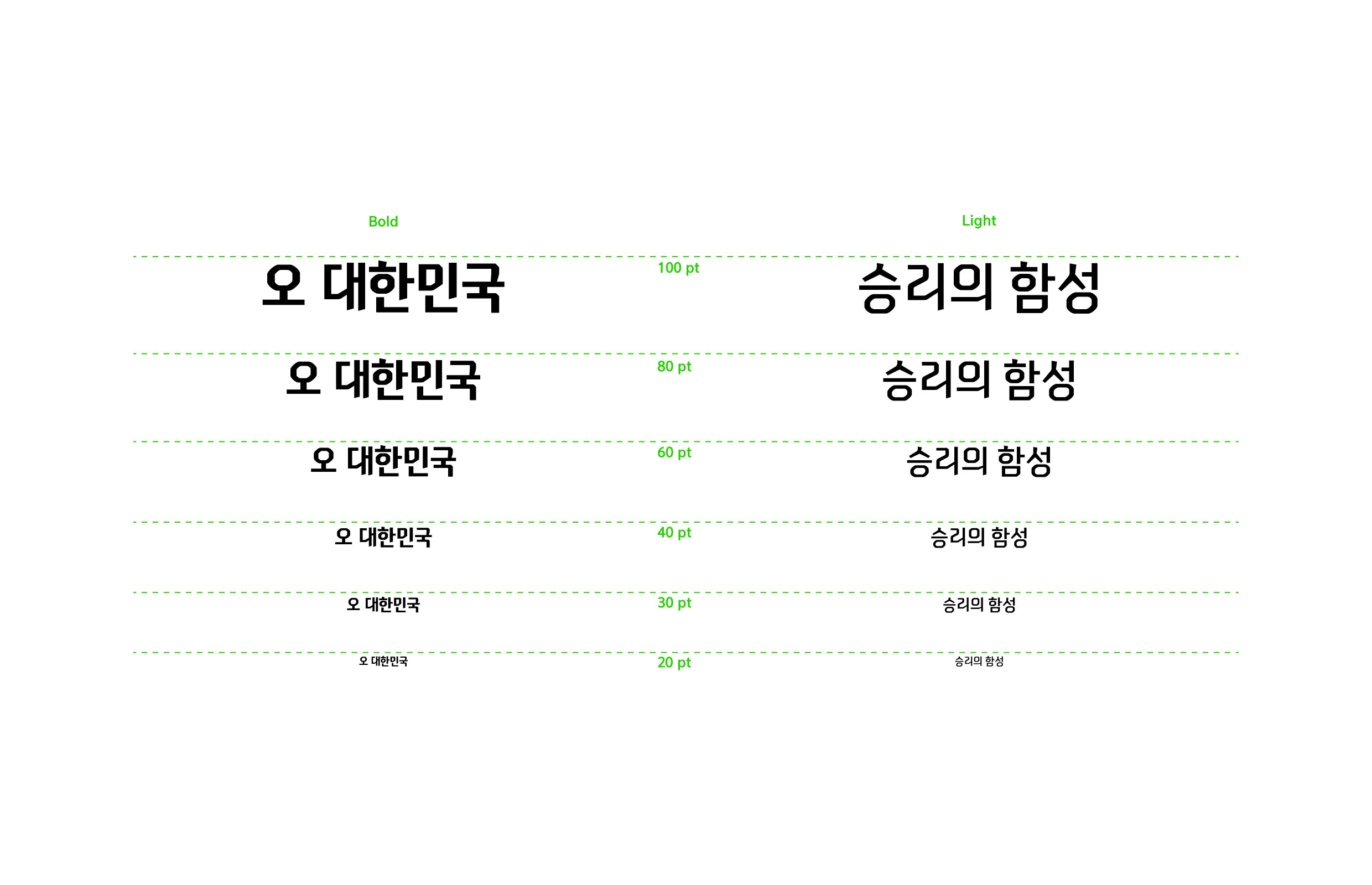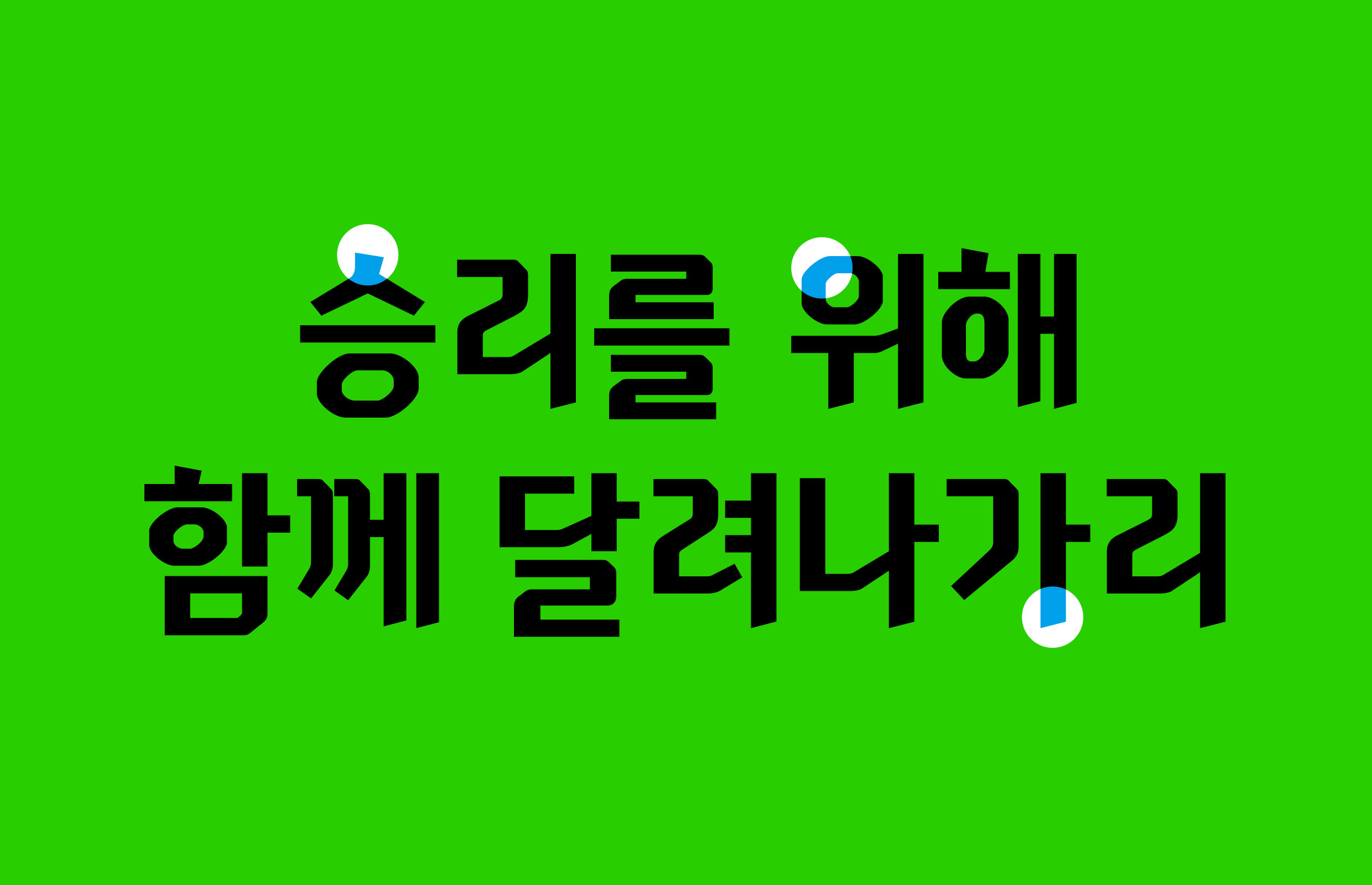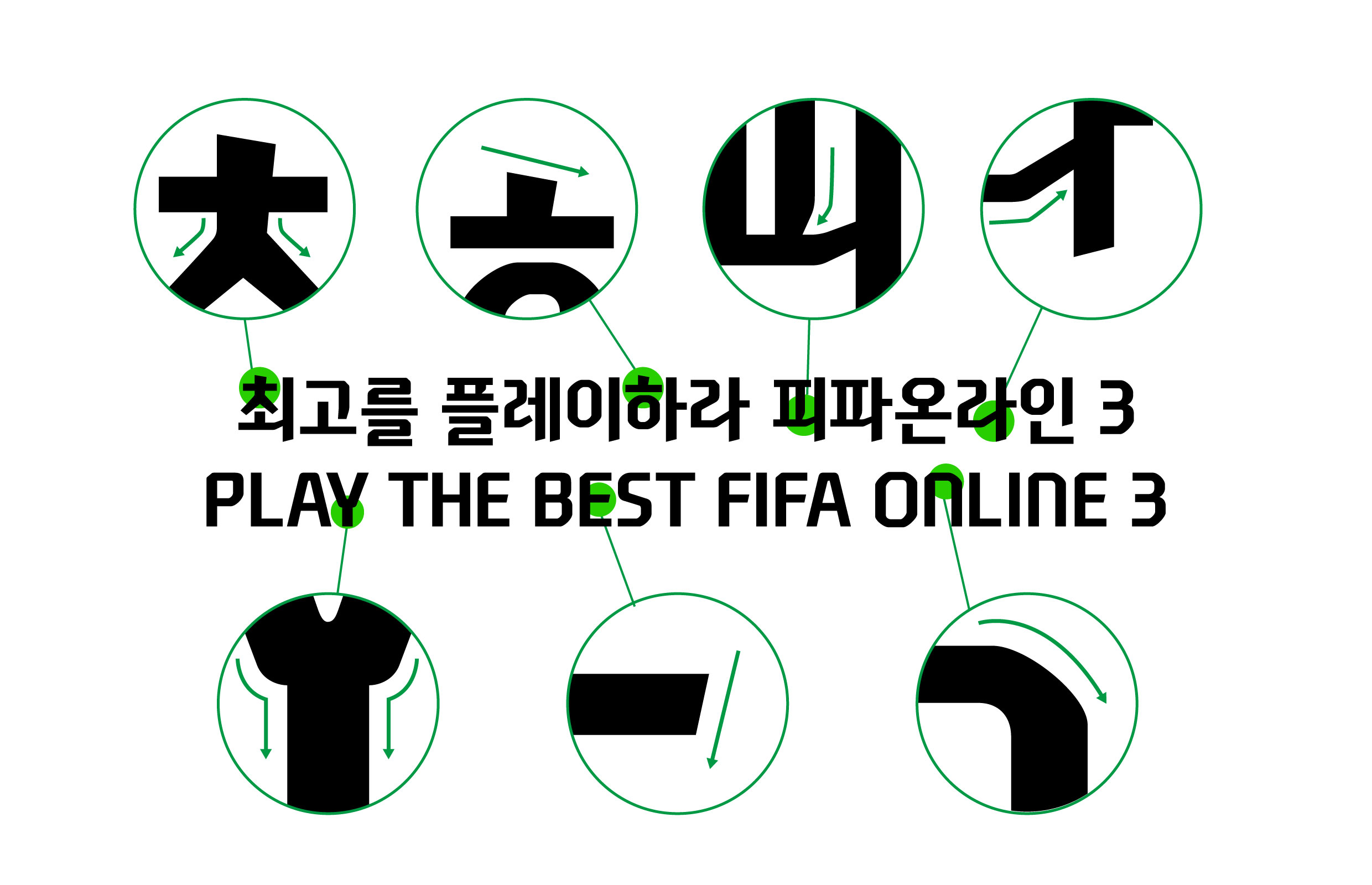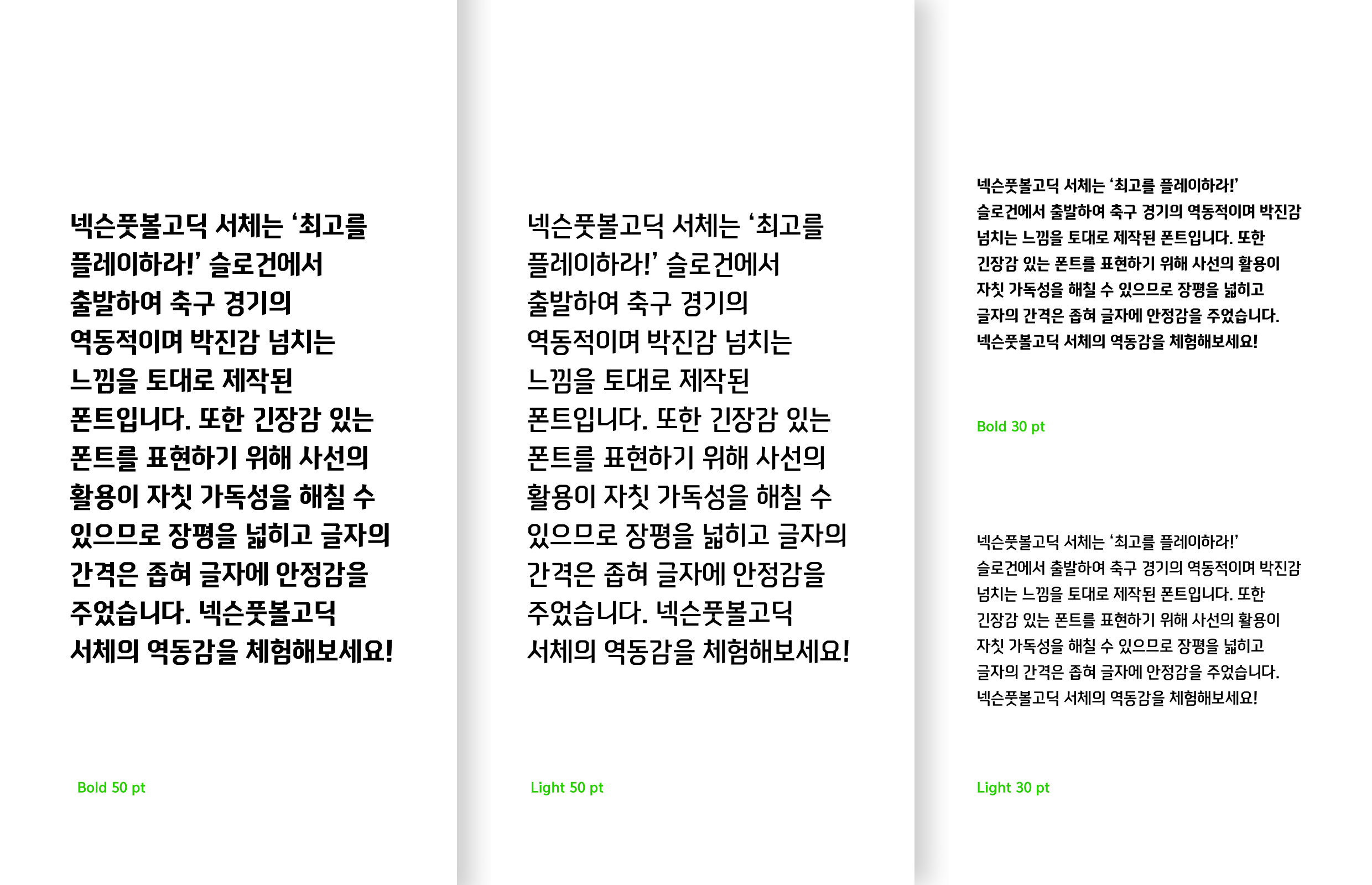
넥슨 [피파온라인3]
넥슨 피파온라인3 [넥슨풋볼고딕]
게임 〈피파온라인〉 시리즈의 슬로건 ‘최고를 플레이하라’에서 출발하여, 축구 경기의 역동적이며 박진감 넘치는 느낌을 글자에 담았다. 역동성과 박진감을 이탤릭 형태로 표현하되, 가독성을 위해 장평을 넓히고 간격은 좁혀 글자에 안정감을 부여했다.